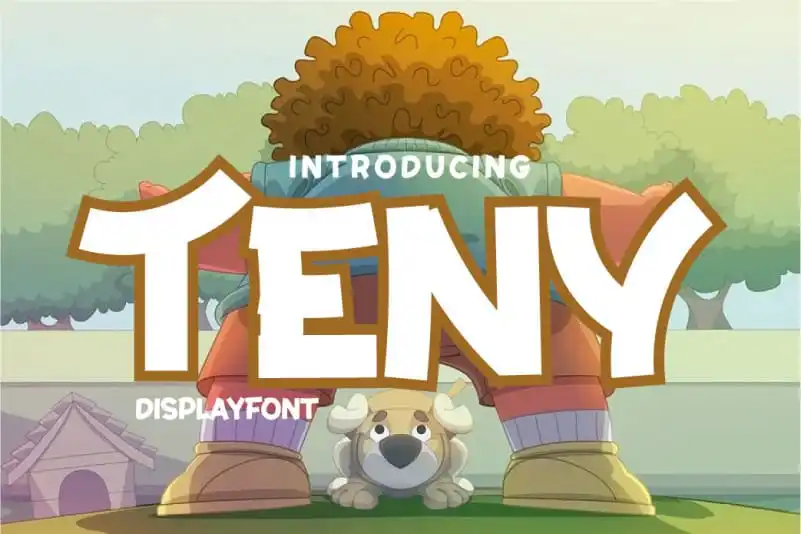
A fonte Teny Display é uma escolha perfeita para designers brasileiros que valorizam a sofisticação e a flexibilidade em suas criações digitais. Ela traz um novo encanto, mantendo as características sólidas e robustas da família original. Seu formato robusto e clean é ideal tanto para projetos de design gráfico quanto para o desenvolvimento de sites e aplicativos. Com seu estilo moderno e elegante, a Teny Display é perfeita para incorporar em diversos tipos de designs, como headlines ou títulos, garantindo sempre um visual elegante e forte em qualquer projeto. Além disso, sua facilidade de leitura, mesmo em formatos menores, faz da fonte uma excelente opção para uso em pequenos espaços de texto, como redes sociais ou materiais digitais. Não perca tempo escolhendo a melhor fonte para seu próximo design!